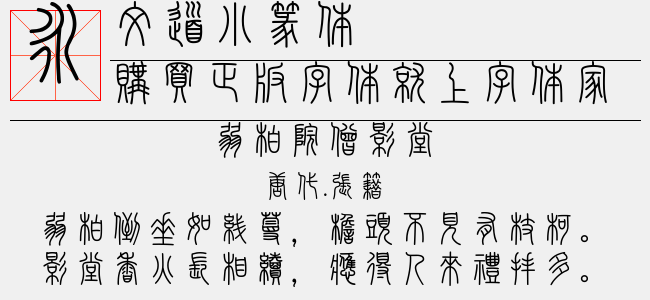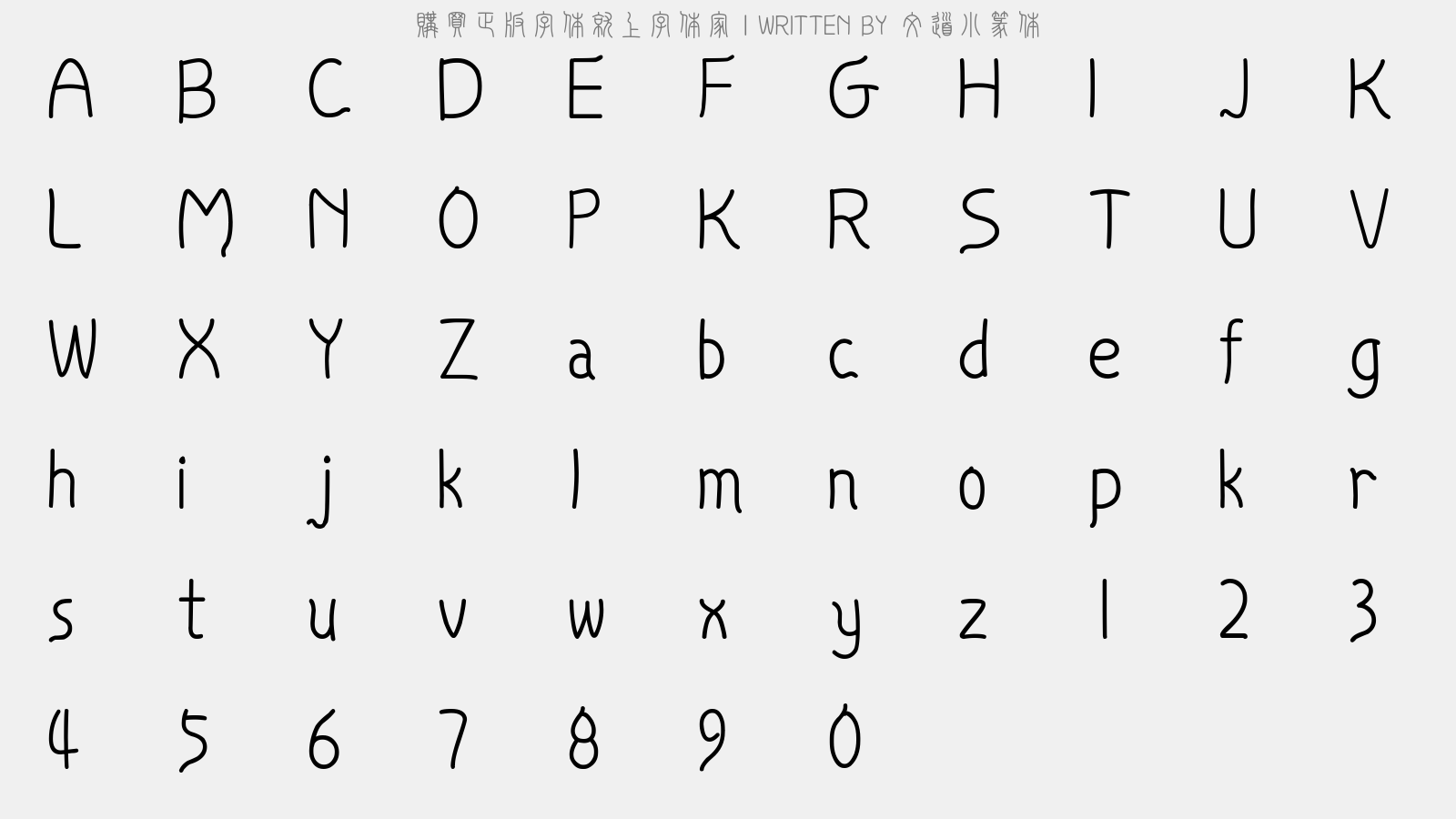
文道小篆体
字体作者:文道字库
字体名称:文道小篆体
字体家族:文道字库
字体公司:文道字库
文道小篆体
文道小篆体是文道字库推出的一款非常不错的艺术字体,风格比一般的字体更有特色,篆书风格,具有很好的视觉感,适合应用于艺术设计、平面宣传设计、网页设计,书法字帖等领域,欢迎喜欢文道小篆体的朋友前来下载使用。